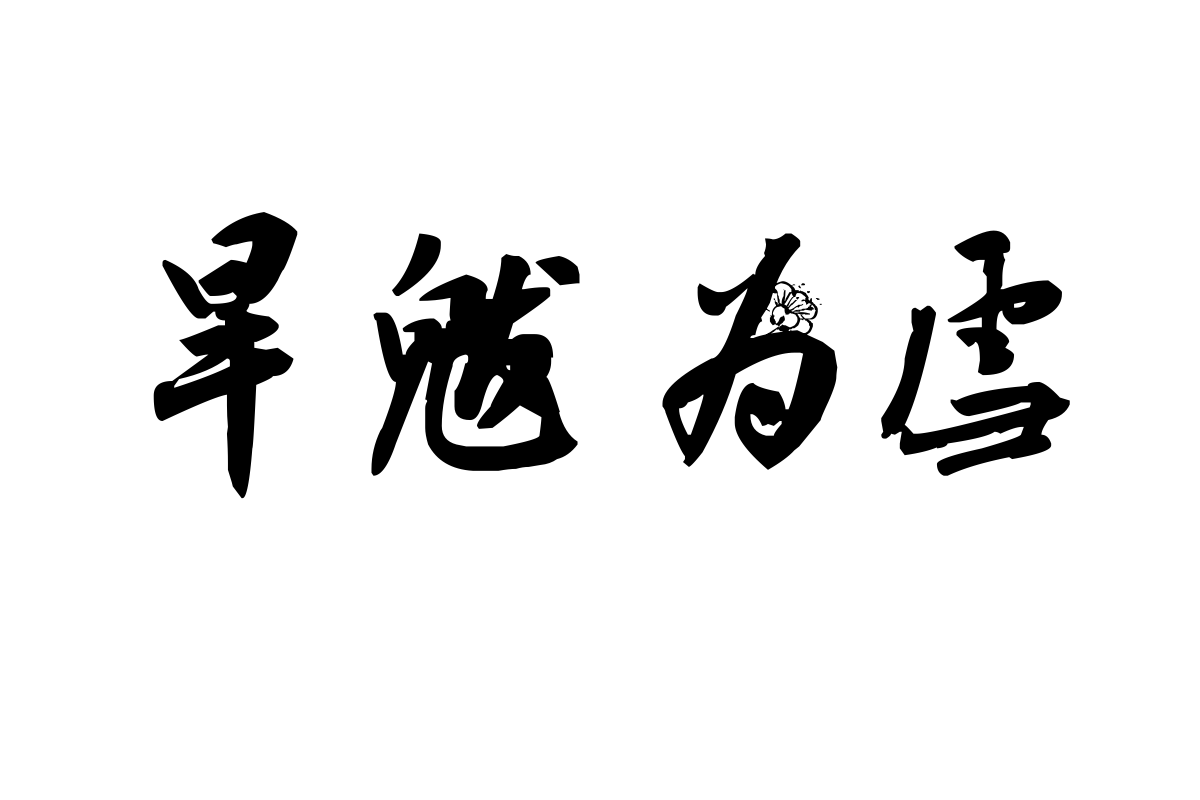
汉呈王天喜墨梅字体是一种书法字体,由汉呈王天喜先生创作。这种字体以其独特的风格和韵味而闻名,深受广大书法爱好者的喜爱。
汉呈王天喜墨梅字体的特点主要体现在以下几个方面:
1. 笔法独特:汉呈王天喜墨梅字体的笔画流畅自然,线条粗细变化丰富,既有力又有韵。这种笔法使得字体显得优雅大方,具有很高的艺术价值。
2. 结构严谨:汉呈王天喜墨梅字体的结构紧凑,字形规整,每个字都有明确的结构和比例。这使得字体具有很强的可读性和辨识度,便于书写和欣赏。
3. 韵味十足:汉呈王天喜墨梅字体的韵味主要体现在其笔触和结字上。笔触细腻柔和,结字饱满圆润,给人一种温馨和谐的感觉。这种韵味使得字体具有很高的审美价值。
4. 形式多样:汉呈王天喜墨梅字体有多种形式,包括楷书、行书、草书等。这些不同形式的字体各有特色,可以满足不同场合和需求的需求。
总之,汉呈王天喜墨梅字体是一种具有独特风格和韵味的书法字体,深受广大书法爱好者的喜爱。